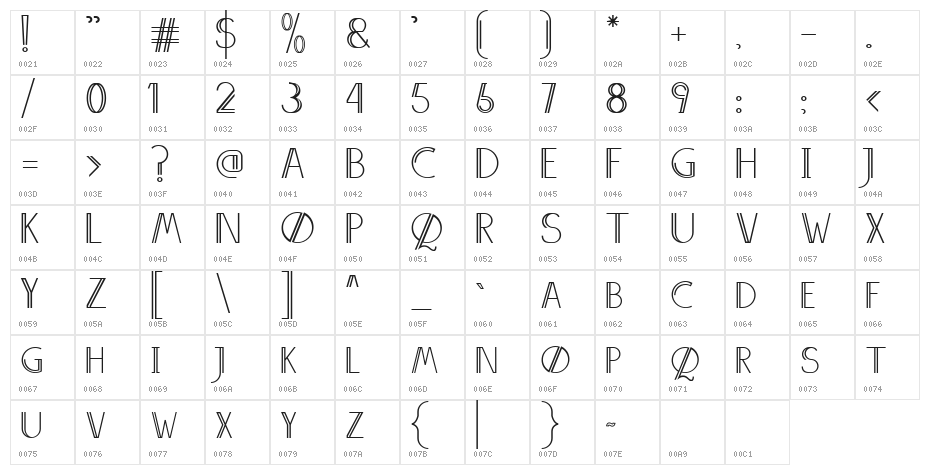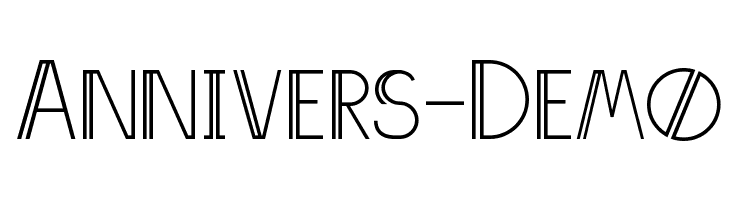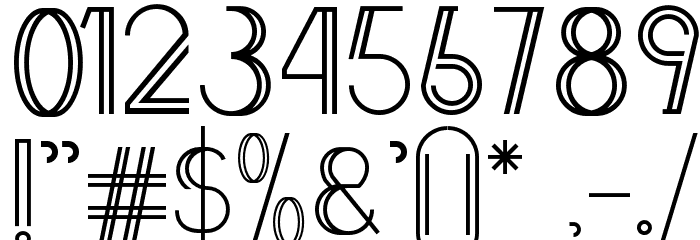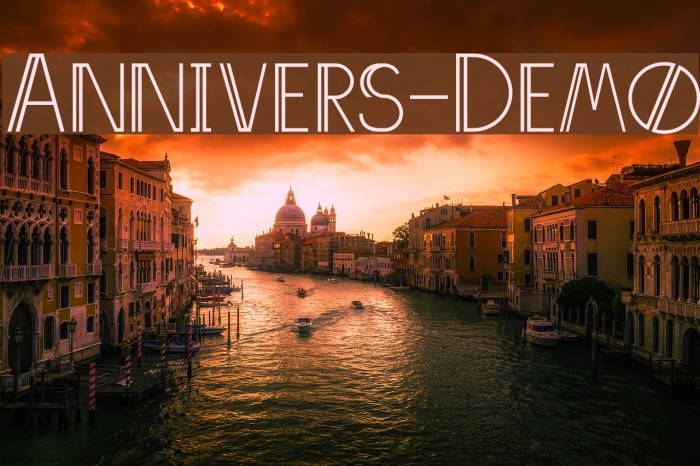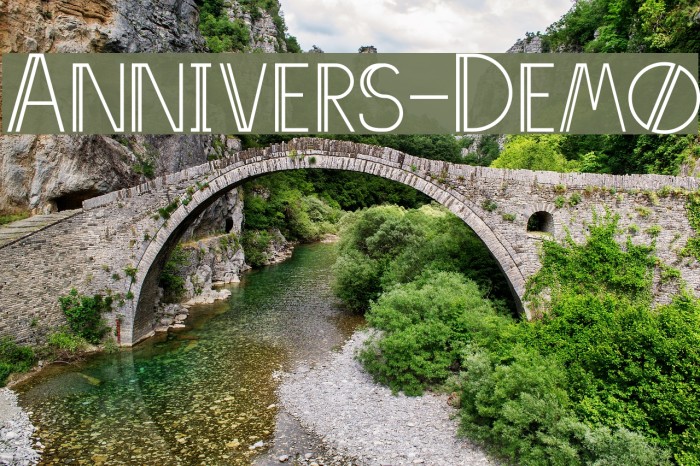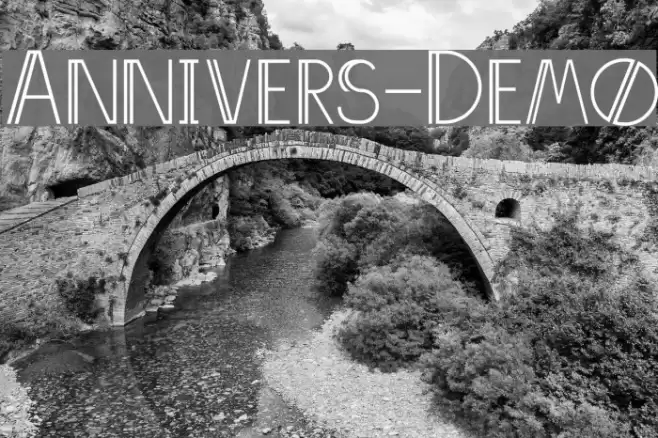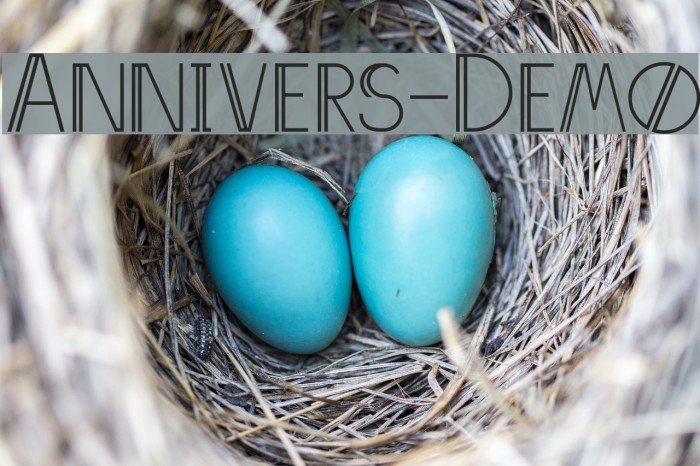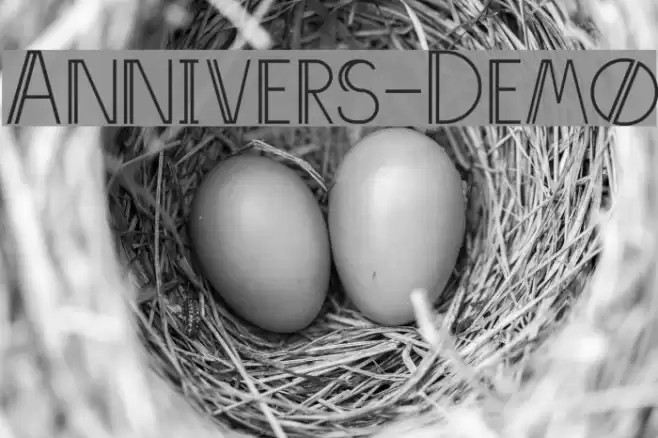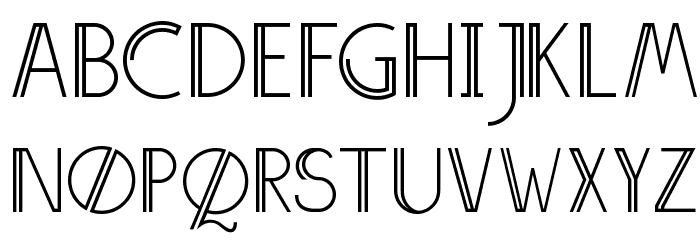
Annivers-Demo Font
✎ Art Deco
| Anwendungsfall | Logos, Headlines, Posters |
| Vorgeschlagene Projekte | Ideal for branding, logos, posters, and editorial design where a modern and sophisticated look is desired. |